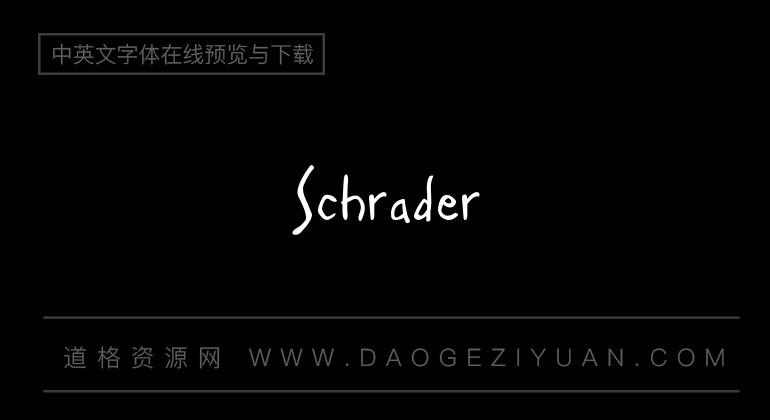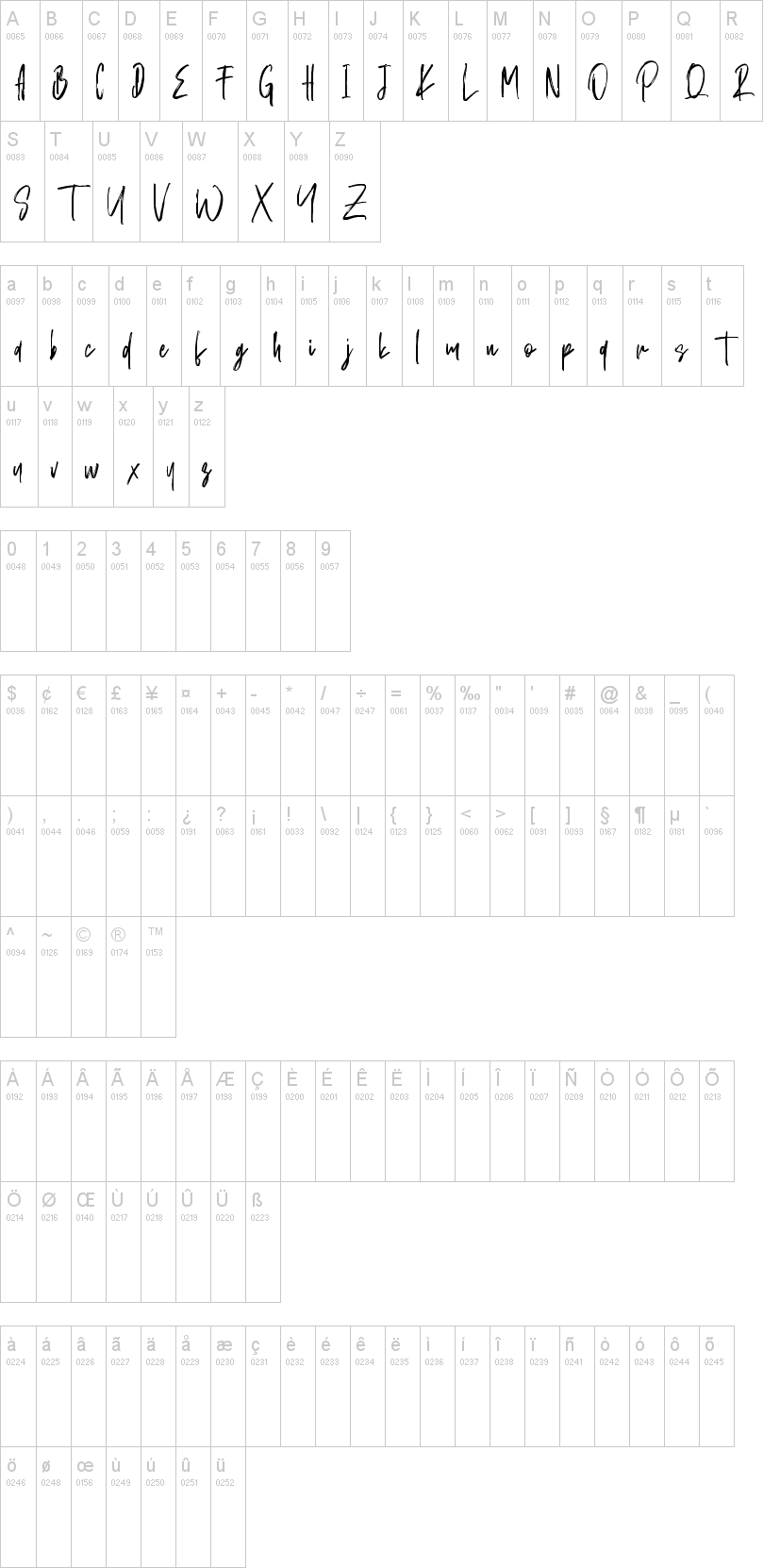
Schrader 是一种经典的排版字体,由德国设计师 Martin Schrader 于1930年代创作。它具有鲜明的英文字母,拥有精致的细节,使用它可以给文字提供更多的质感和美感。此外,Schrader 字体可以让文字更加清晰,使得文字更加容易阅读,同时也提供了更多的设计空间,可以让设计师更自由地表达自己的想法。内容介绍
Schrader是一款非常不错的手写艺术字体,具有很好的视觉感,适合于文化类的宣传设计、商业类品牌的广告和产品包装设计以及个性化文字排版等较多场景。